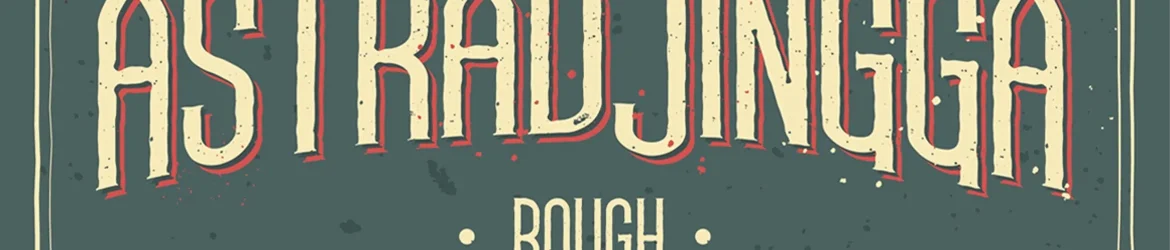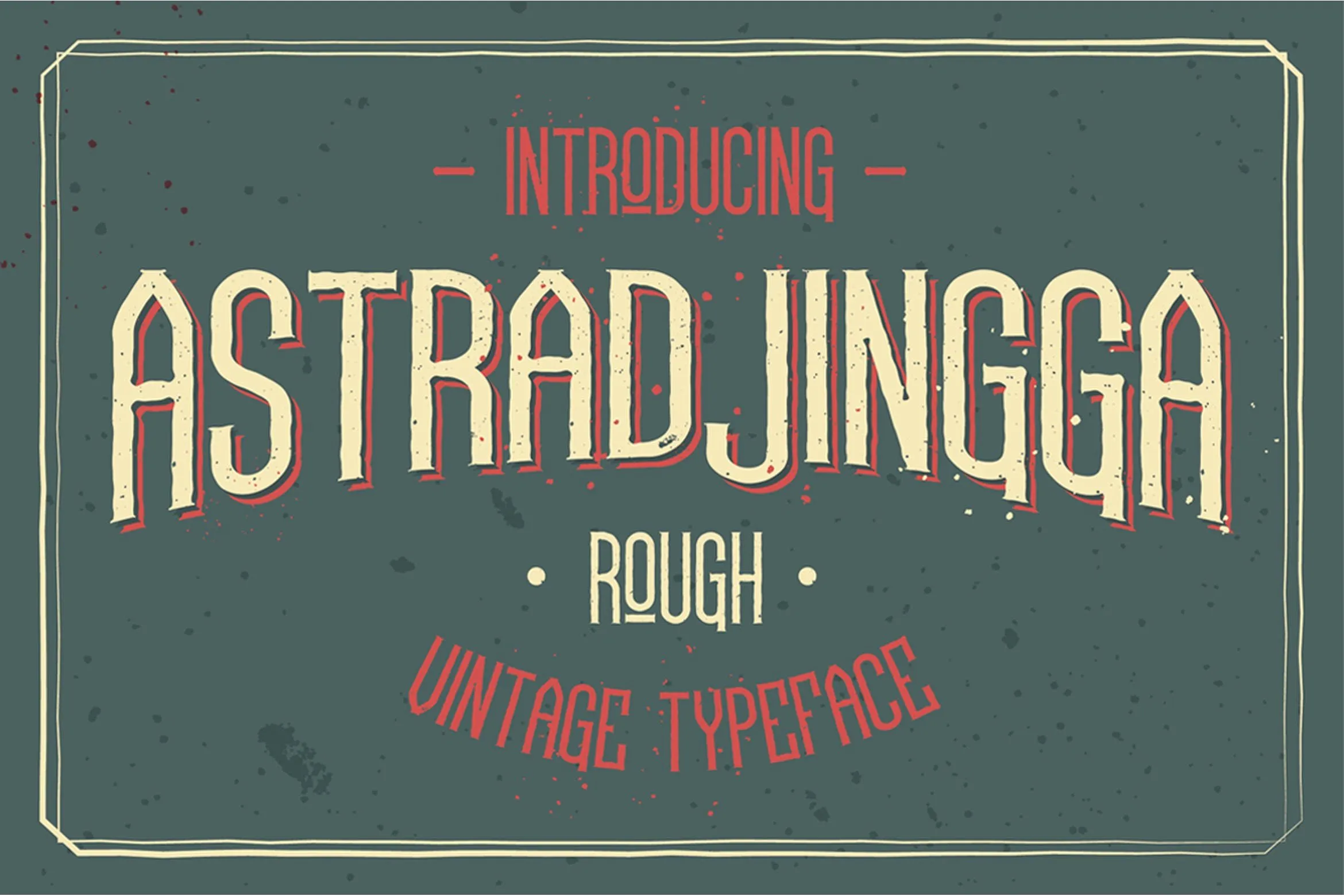
Astradjingga Rough Font
A Astradjingga Rough é uma elegante fonte serif vintage com traços grossos e marcantes. Suas linhas suaves e robustez criam um contraste interessante, tornando-a perfeita para projetos que buscam sensações nostálgicas e personalizadas. Esta fonte é especialmente apropriada para aplicações em logotipos, embalagens de produtos, rótulos e design para lojas antigos, bares, ou qualquer projeto que deseje destacar características de eras passadas. A combinatória desta fonte com outros elementos permite criar uma atmosfera vintage vibrante. É perfeita para aqueles buscando manter a essência nostálgica em seus projetos design contemporâneos. Ideal tanto para designers como para os que desejam dar um toque especial às suas criações, sem sair do tema retro ou vintage. Esta fonte de Hamilton é uma opção versátil e inspiradora.